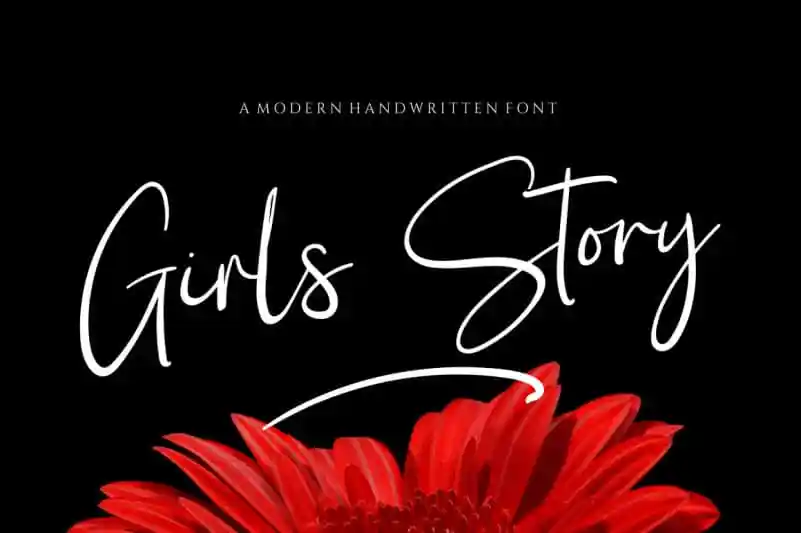
Girl Story Signature Script Font – Download Grátis
A Girl Story Signature Script Font é uma fonte escrita a lápis delicada e elegante, perfeita para personalizar textos com estilo. Seus caracteres distintos e bem arredondados fazem dela um verdadeiro trabalho de arte. Esta fonte suporta PUA (Propriedades Unicode Avançadas), o que significa que você pode facilmente acessar todos os sinais e ascentes com toda a sua facilidade. Descubra a beleza única desta fonte enquanto ela adiciona um toque autêntico ao seu trabalho de design. Ao instalar ou usar esta fonte, você concorda com o Termo de Uso do Produto: As regras incluem manter os direitos autorais da fonte e não fazer uso comercial sem permissão especial. Além disso, é importante garantir que a fonte seja usada apenas para propósitos pessoais ou projetos de arte individual, evitando o uso para fins comerciais. Descubra agora como esta Girl Story Signature Script Font pode personalizar seu projeto de design de forma única e elegante.